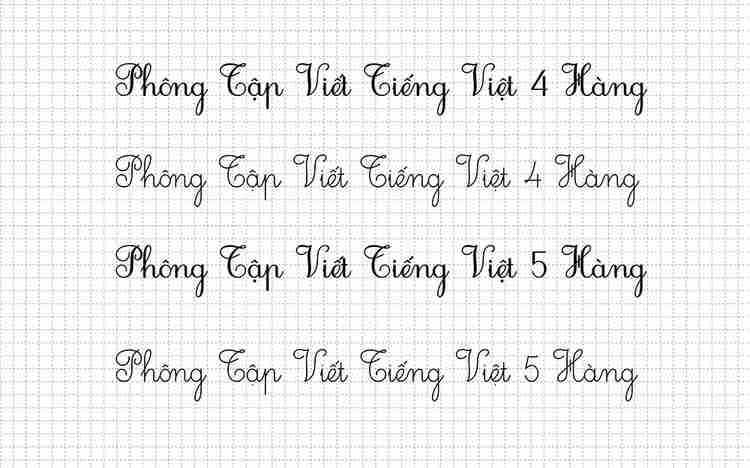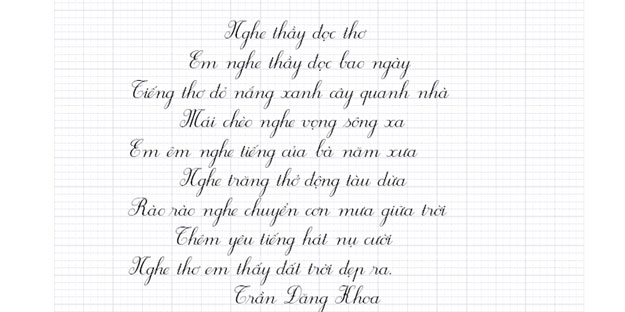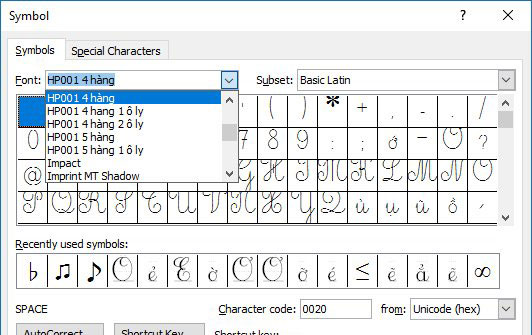
Hoatieu.vn xin gửi tới bạn đọc bài viết mẫu font chữ tập viết tiểu học để bạn đọc cùng tham khảo. Mẫu font chữ tập viết tiểu học với những mẫu font chữ chuẩn và đẹp theo HP001 (2.0) để thầy cô cho các em học sinh luyện viết hàng ngày. Mời thầy cô cùng tham khảo chi tiết và tải font chữ tiểu học miễn phí tại bài viết.
Font chữ tập viết tiểu học HP001 4 hàng, 5 hàng
Khác với các font chữ thông thường, font chữ tiểu học có ô ly với các chữ viết mô phỏng chữ viết tay đạt chuẩn là bộ font tiếng Việt luyện viết cho trẻ em. Bộ font tập viết này được sử dụng để luyện viết cho học sinh lớp 1 và tiểu học. Font chữ tập viết đẹp dành cho tiểu học cũng là Font chữ nằm trong bộ chữ tiếng Việt; các kiểu chữ viết tiểu học được soạn thảo theo Font chữ chung của Bộ Giáo Dục đào tạo. Ngoài ra, để giúp phụ huynh, học sinh cùng thầy cô sử dụng font chữ tiểu học dễ dàng, bài viết này cũng sẽ cung cấp hướng dẫn cách cài phông chữ tiểu học đơn giản, nhanh chóng. Mời các bạn tham khảo.
1. Font chữ tập viết tiểu học là gì?
Font chữ tập viết Tiểu học là bộ font tiếng Việt chuẩn để giáo viên soạn thảo các tiết chính tả để cho học sinh luyện viết chữ. Đây là bộ font phổ biến hoàn toàn tương thích với bộ mã của Unikey hay Vietkey. Font chữ tập viết tiểu học sẽ có ô ly hoặc không (tùy ý thích khi sử dụng của bạn) cùng các chữ viết mô phỏng chữ viết tay đạt chuẩn, được sử dụng trong các chương trình giáo dục Tiểu học.
Đây là Font chữ hữu ích này bố mẹ cũng có thể sử dụng cho các em ôn luyện, luyện viết chữ đẹp tại nhà, luyện viết chữ đẹp cho các bé.
2. Mẫu font chữ tập viết tiểu học